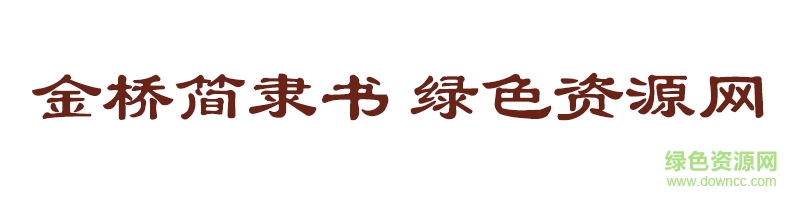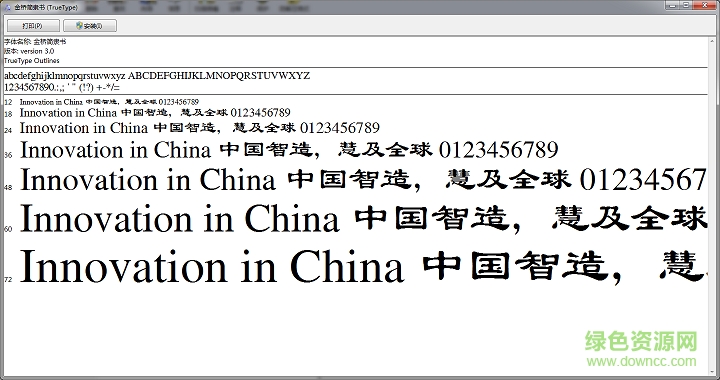
金橋簡(jiǎn)隸書(shū)是一款筆畫(huà)偏粗的簡(jiǎn)體隸書(shū)字體。因?yàn)槭请`書(shū)的緣故,字體給人的感覺(jué)比較典雅,美感十足,書(shū)寫(xiě)的文字非常優(yōu)美。趕快來(lái)綠色資源網(wǎng)下載體驗(yàn)吧!
金橋簡(jiǎn)隸書(shū)字是漢字由篆書(shū)演變?yōu)殡`書(shū)的過(guò)程形成的字體。字型變圓形為方形,線條變弧線為直線,筆畫(huà)變繁雜為簡(jiǎn)省,徹底筆畫(huà)化。隸變是古今漢字的分水嶺。適用于畫(huà)冊(cè)設(shè)計(jì),海報(bào)設(shè)計(jì),圖書(shū)印刷等廣告設(shè)計(jì)場(chǎng)合使用。